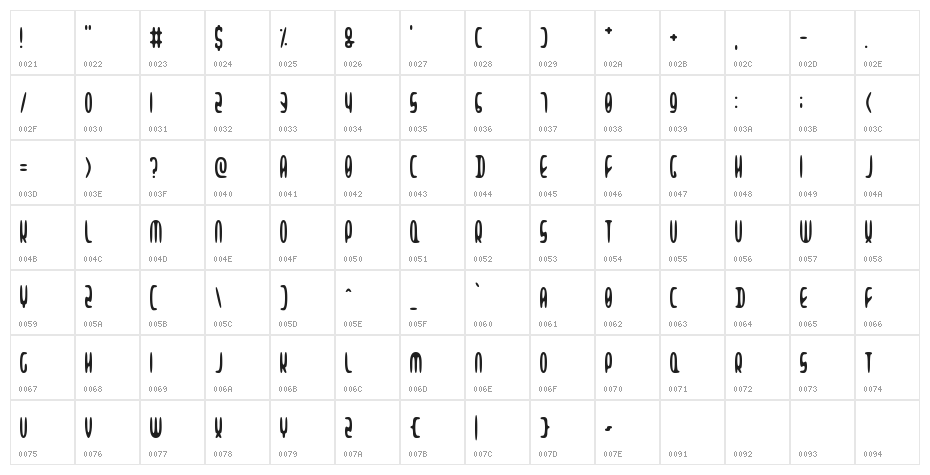
Alien Beasts Font
| Рекомендуемые проекты | Ideal for posters, album covers, children's books, and branding that seeks a unique and playful aesthetic. |
Alien Beasts